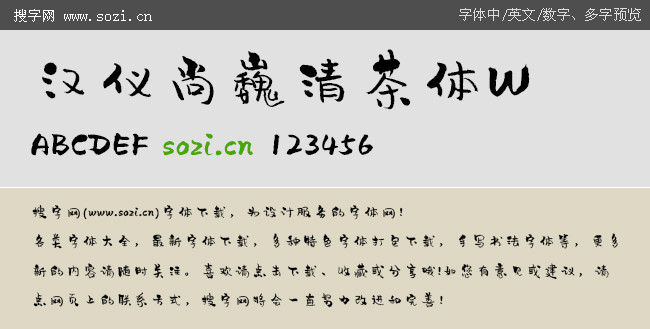
漢儀尚巍清茶體W
搜字網(wǎng)給大家提供一款漢儀尚巍清茶體W中文字體下載,尚巍清茶體將部分筆畫加粗,顯得非常童趣可愛,整體效果比較天真浪漫,適合應(yīng)用于藝術(shù)設(shè)計(jì)、平面宣傳設(shè)計(jì)、網(wǎng)頁設(shè)計(jì)等應(yīng)用。(本字體為個(gè)人非商用版,如需要商用請(qǐng)聯(lián)系漢儀公司購買版權(quán))